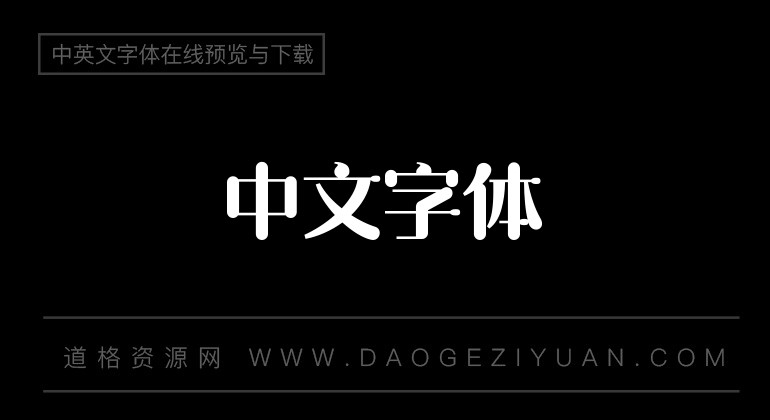
海派腔调明姿简
海派腔调明姿简字体是一款以海派腔调为特色的汉字字体,它具有明朗的设计,简洁的线条,清晰的结构,给人以清新、轻松的感觉。海派腔调明姿简字体的特点是汉字的形状设计简洁而优美,笔画细腻,线条流畅,给人以清新、轻松的感觉,适合用于广告、标识、印刷等多种场合。
海派腔调明姿简是一款非常不错的手写艺术字体,具有很好的视觉感,适合于文化类的宣传设计、商业类品牌的广告和产品包装设计以及个性化文字排版等较多场景。